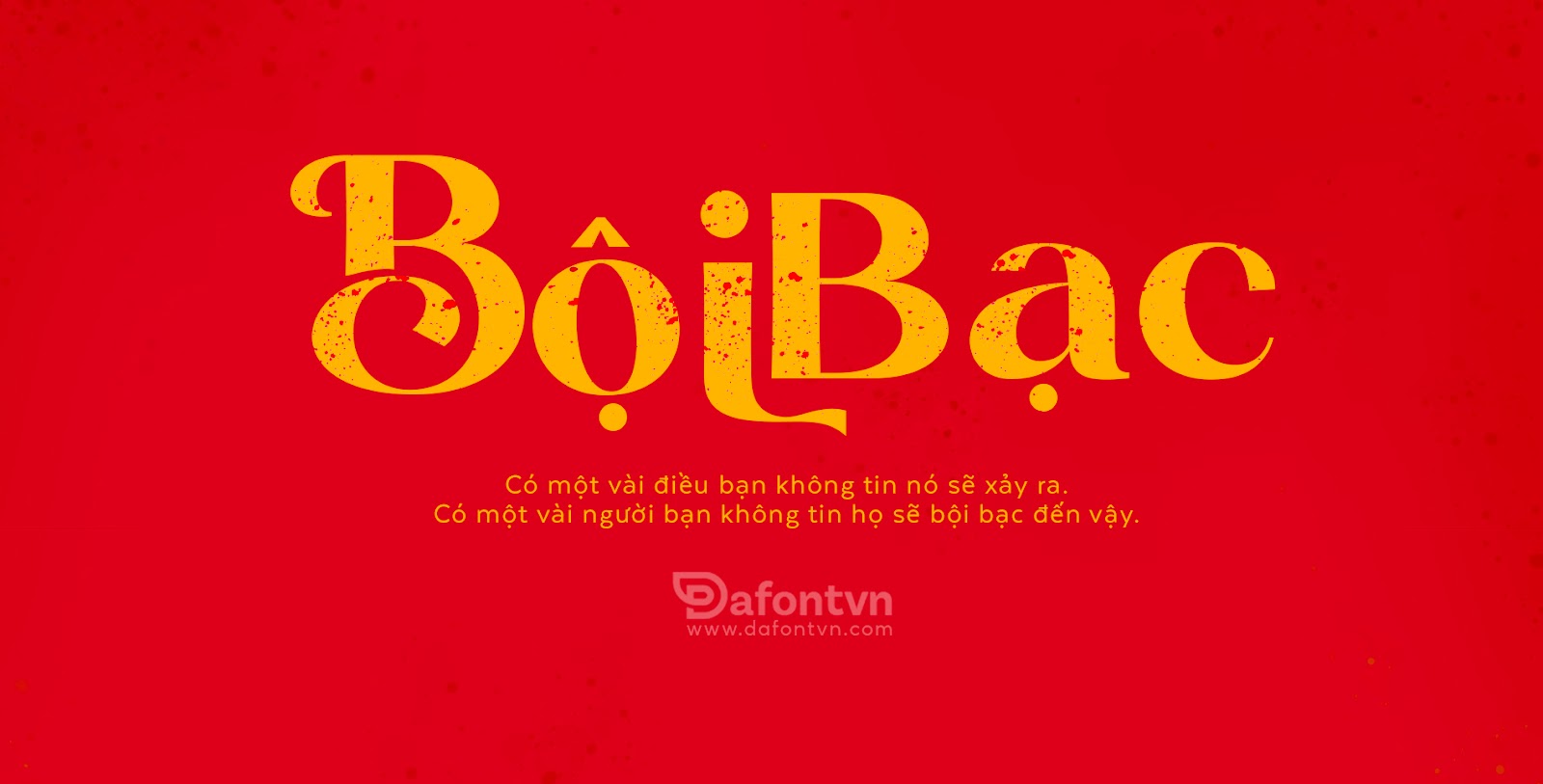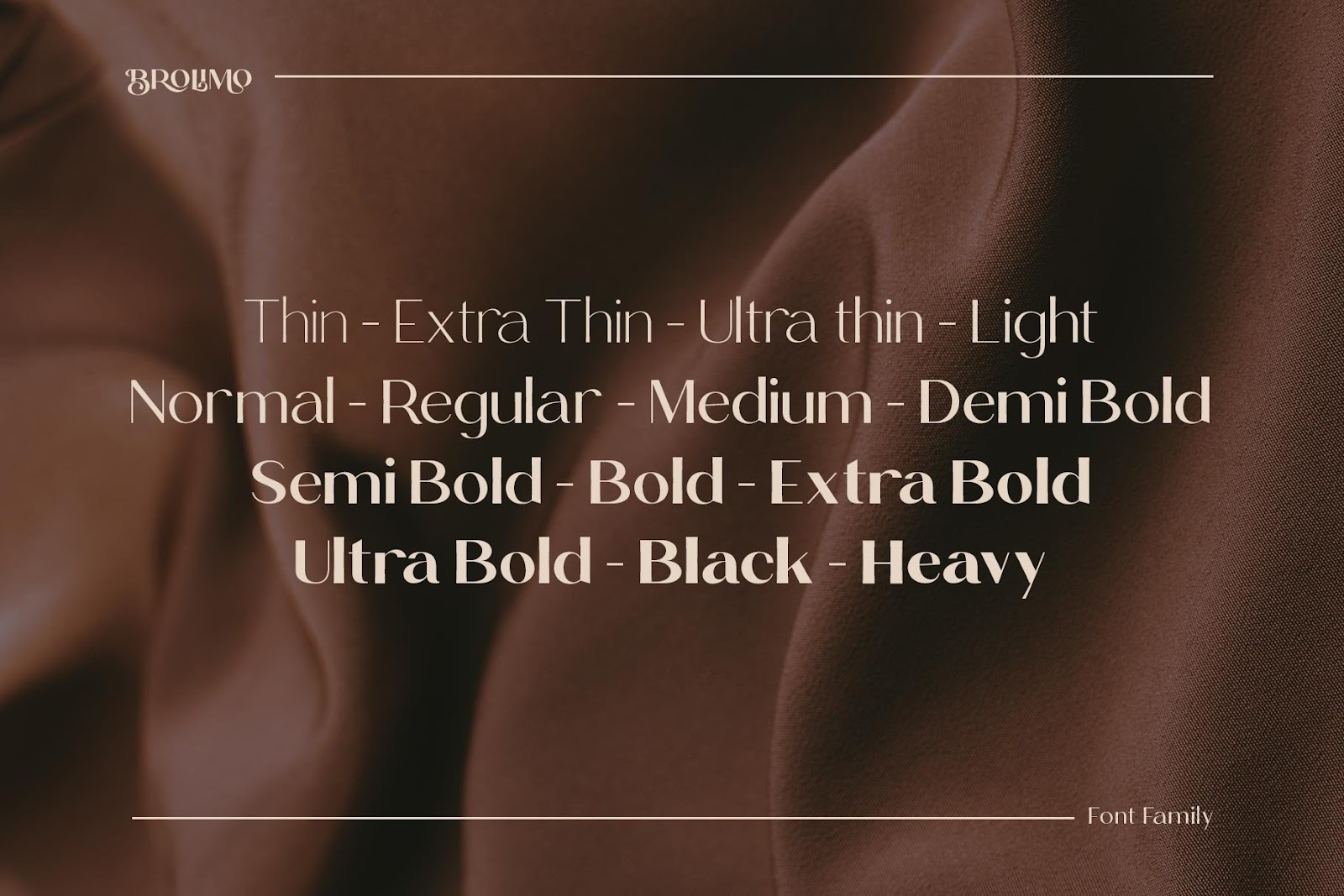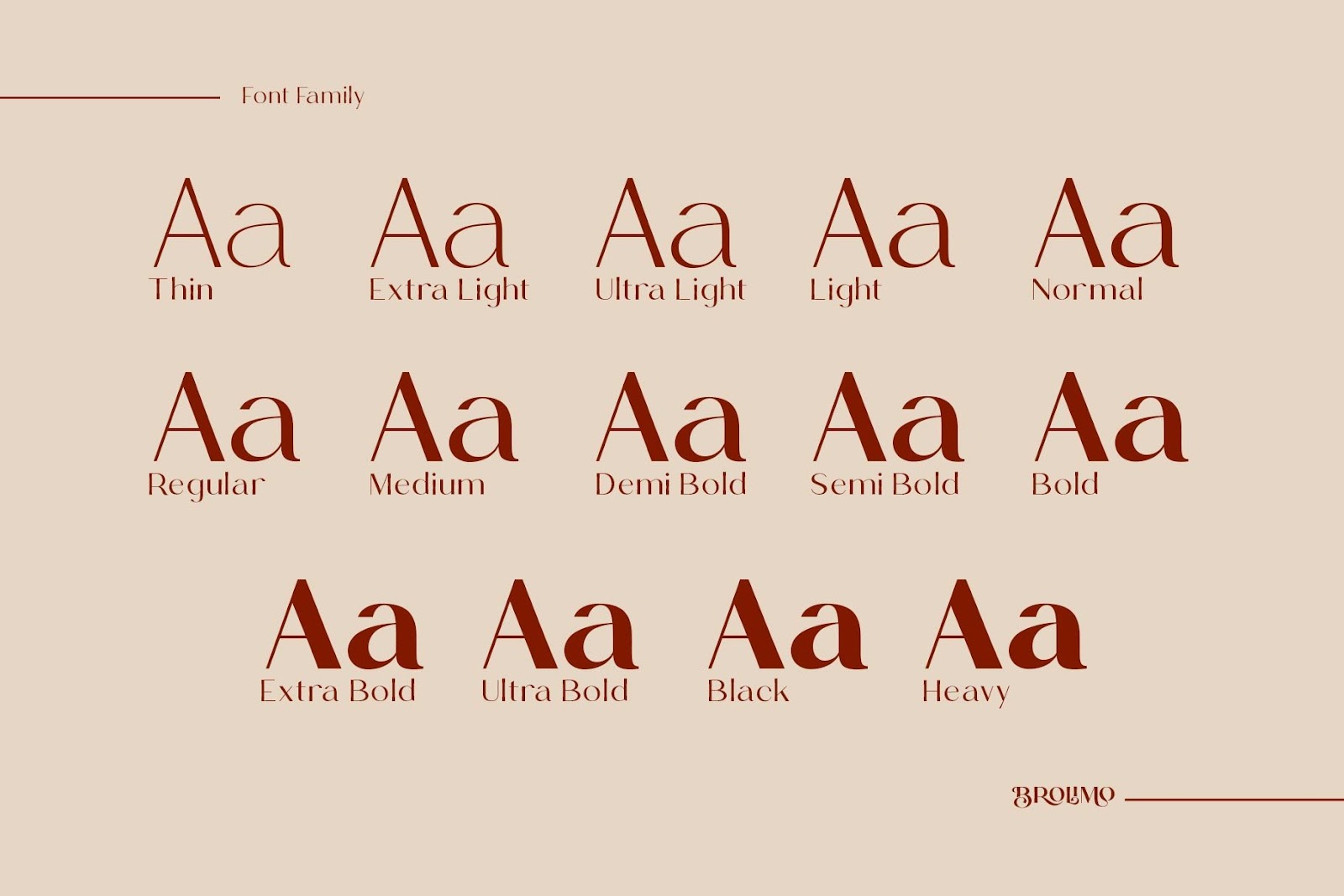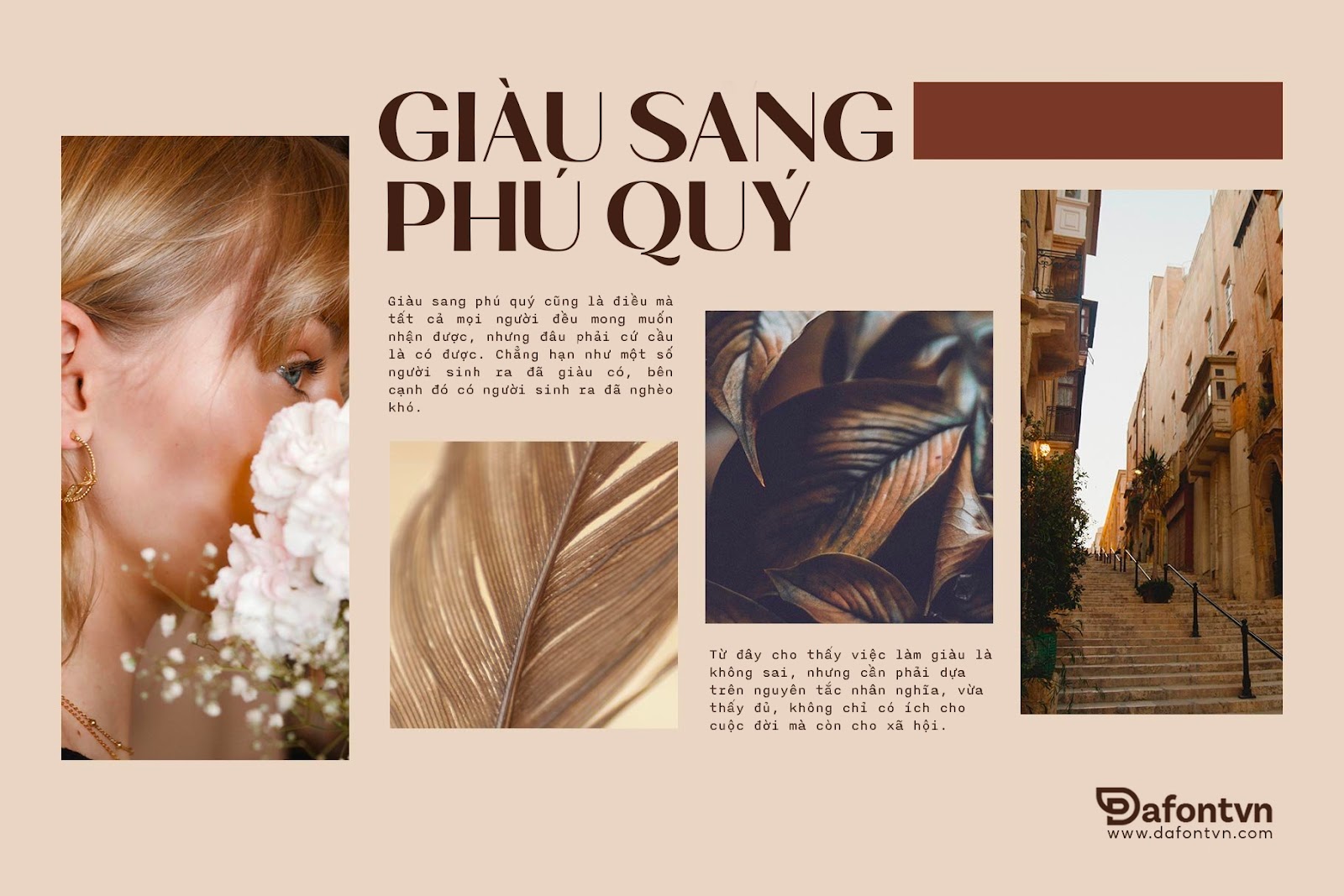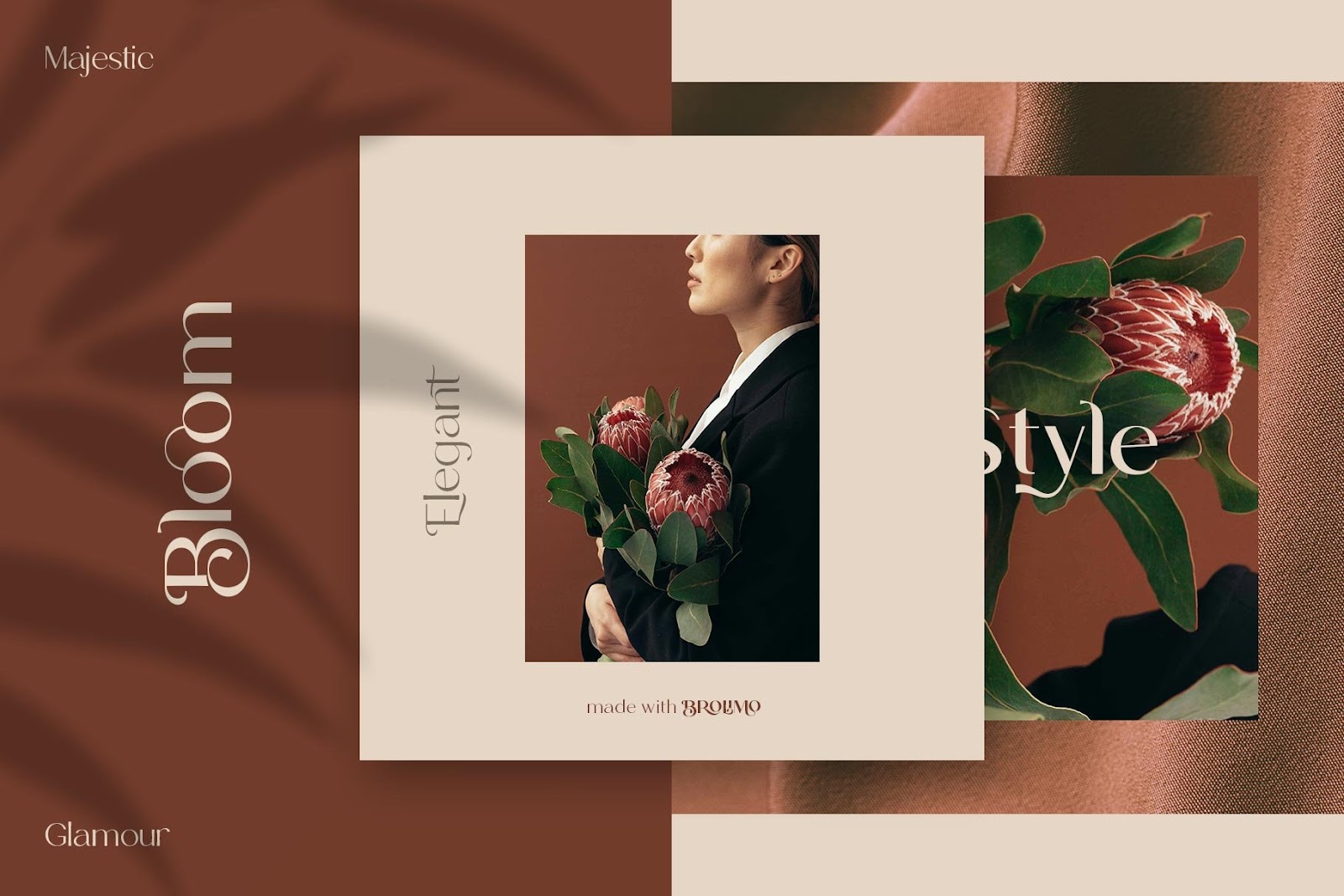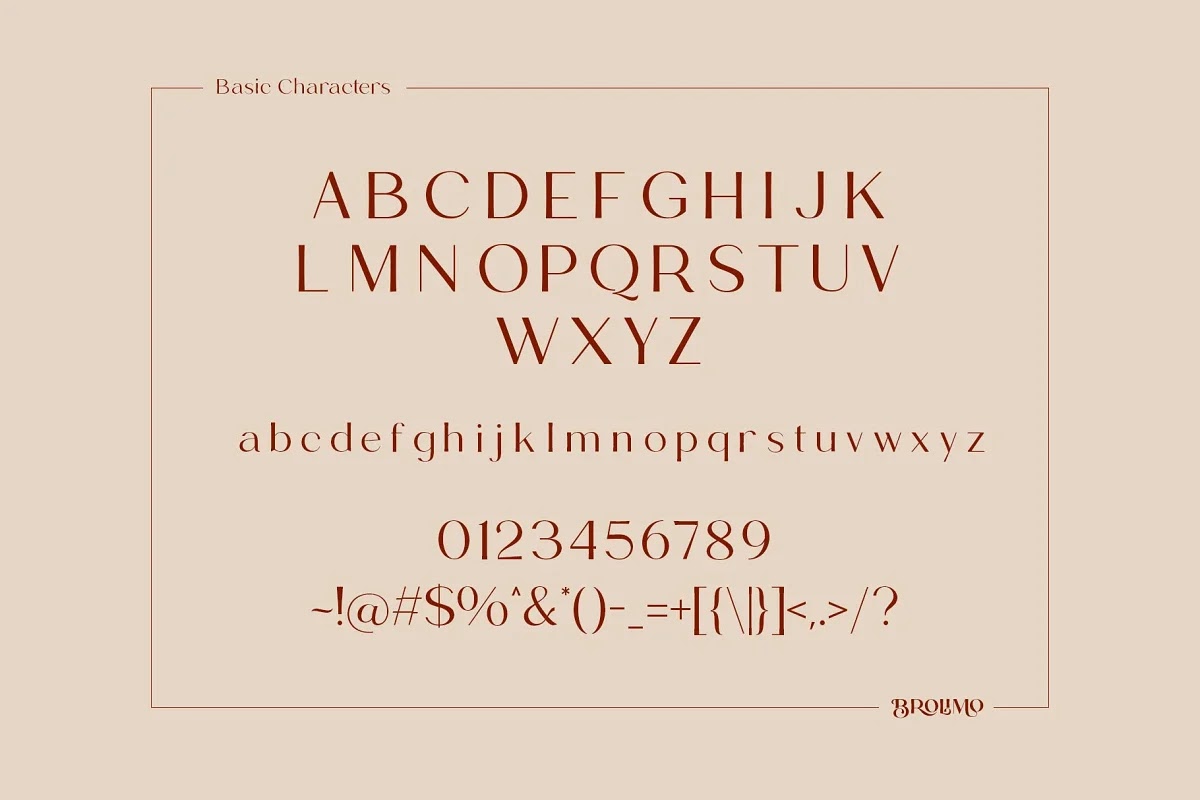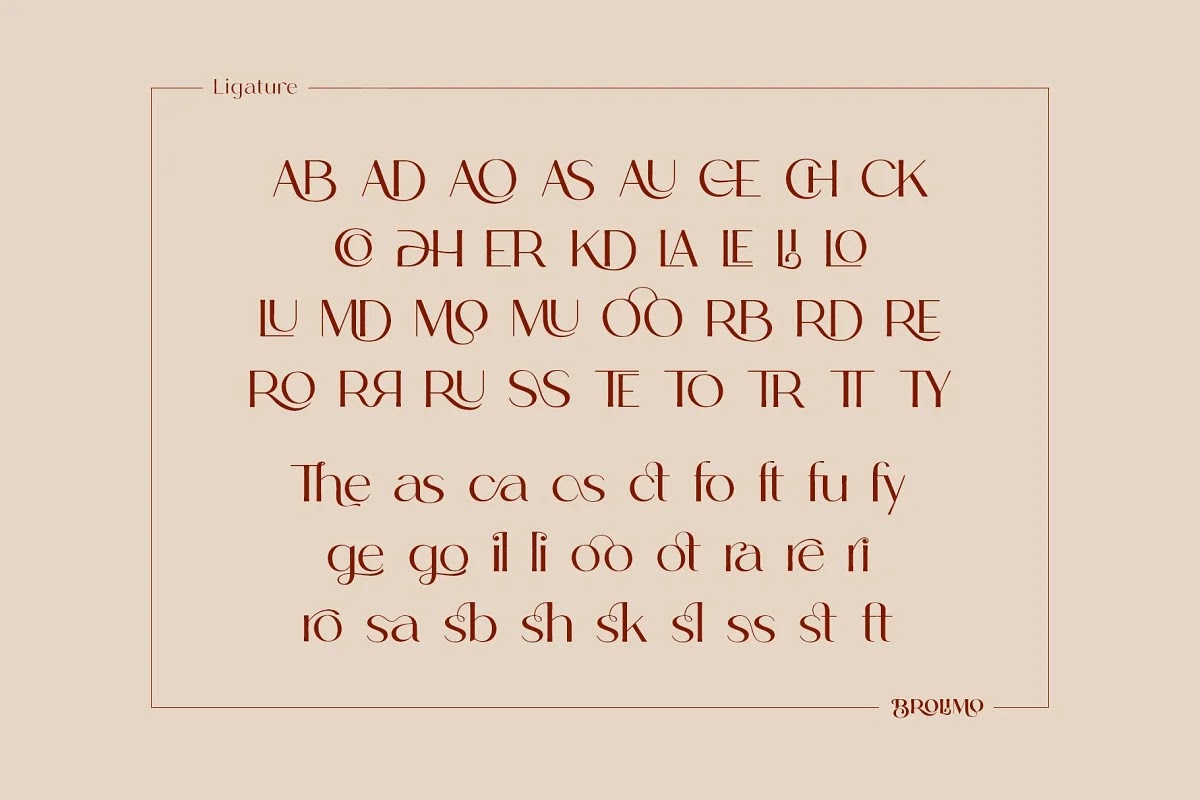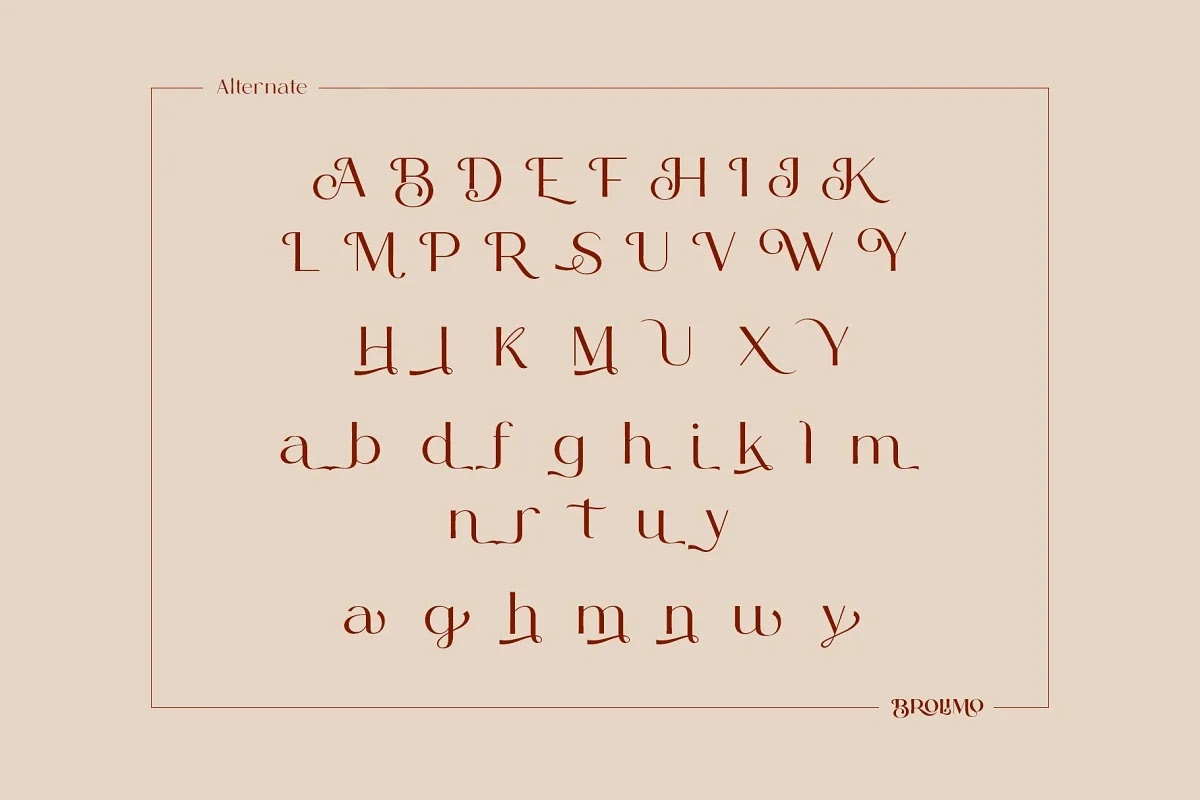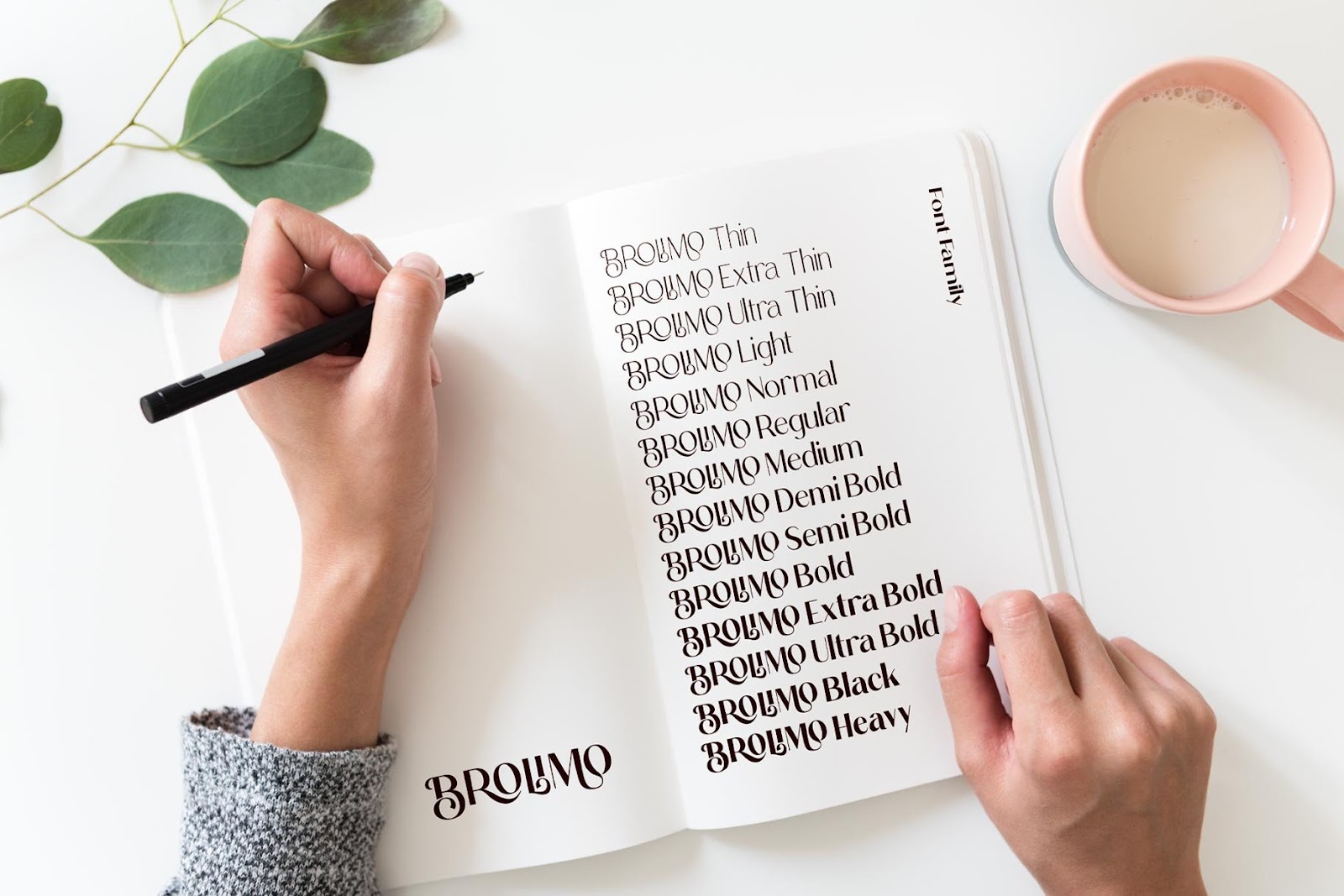
Trọn bộ font Brolimo Việt Hóa chất lượng
BROLIMO font family bao gồm 14 kiểu từ Thin cho đến Heavy. Bộ font chữ hiện đại và thanh lịch sẽ giúp bạn tạo ra một thiết kế độc đáo. Bên cạnh sự độc đáo, font Brolimo còn có nét đơn giản sang trọng làm cho các thiết kế trở nên quyến rũ và gợi cảm.
Ngoài ra, bộ font Brolimo Việt Hóa đi kèm với rất nhiều glyphs để giúp bạn kết hợp tạo ra các thiết kế hoàn hảo hơn nữa, phù hợp cho các thiết kế như xây dựng thương hiệu, bìa sách, báo chí, tạp chí, tiêu đề, giới thiệu sản phẩm…